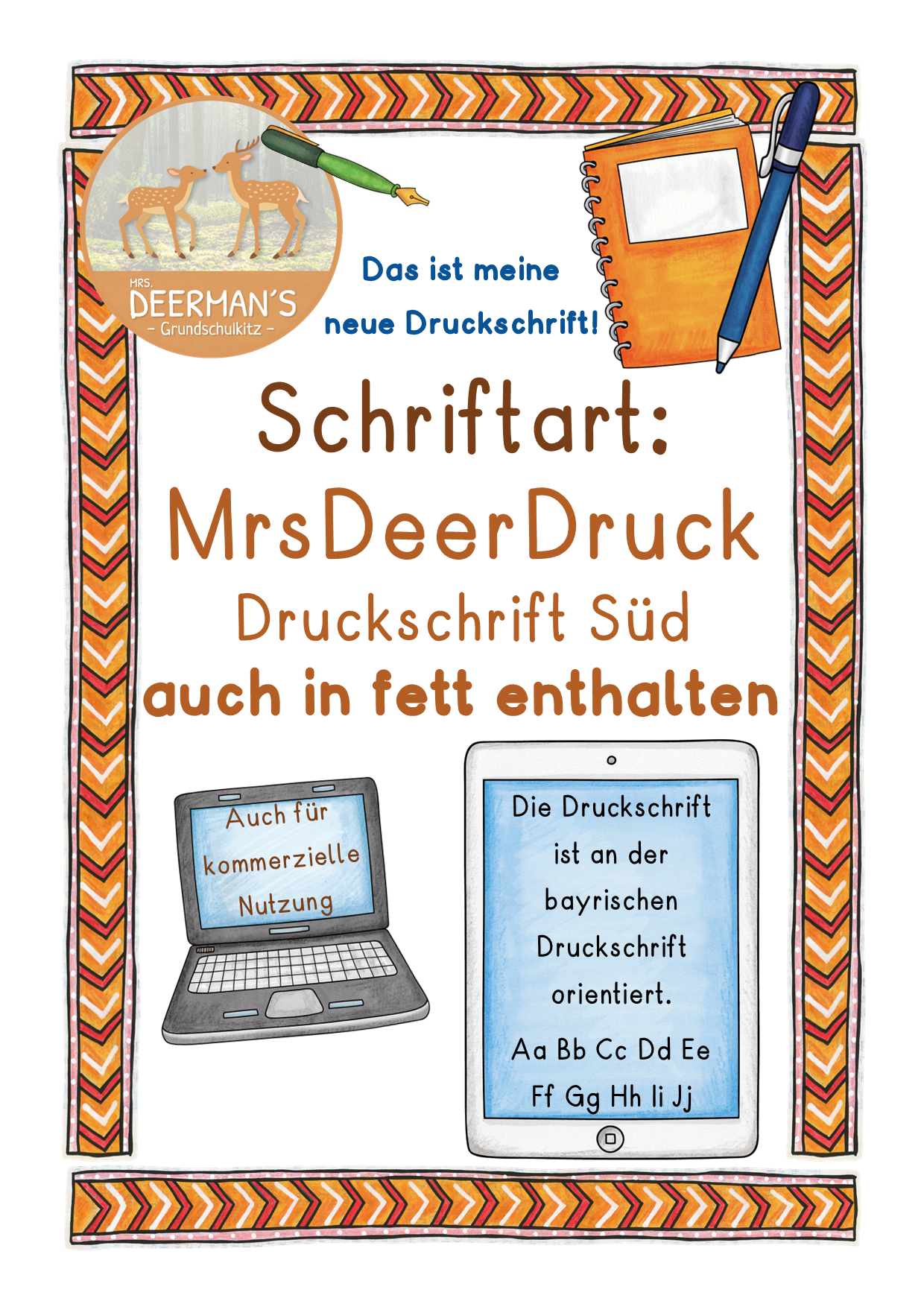
Tolle Schrift
Ich bin bei Schriften sehr wählerisch. Mir ist wichtig, dass die Buchstaben für die Kinder gut lesbar sind, das Gesamtbild gleichzeitig aber auch ästhetisch ansprechend aussieht.
Die Schrift MrsDeerDruck ist top! Bin sehr zufrieden. :)
Ich liebe diese Schriftart!
Ich mag die Schriftart sehr, sie ist für Erst- und Zweitklässler gut lesbar. Danke!
Jetzt macht die Materialerstellung noch mehr Spaß! 🤩 Die Schrift ist so hübsch und für die SchülerInnen gut lesbar! Vielen Dank für das extra "G" für mich. 🫶🏼
Wunderschön und klare Buchstaben und Zahlen, sogar mit den ersten gängigen Brüchen!
Diese Schrift ist sehr schön und klar gestaltet.
Sie hat sogar das große G in einer zusätzlichen Version ergänzt, welche nun ebenfalls als ZIP dabei ist. Vielen Dank dafür!
Ich freue mich sehr diese Druckschrift einzusetzen und freue mich schon, wenn die Grundschrift im gleichen Stil weiter geführt wird.
Klare und trotzdem individuelle Schrift
Schon lange in Nutzung
Eine super Schrift für die Kinder. Sie können diese bereits im Anfangsunterricht lesen. Ich benutze sie nun schon einige Monate und sie sieht im Gesamtbild zusätzlich noch toll aus. Danke dafür! lg Claudia - Frau Zauberfuchs